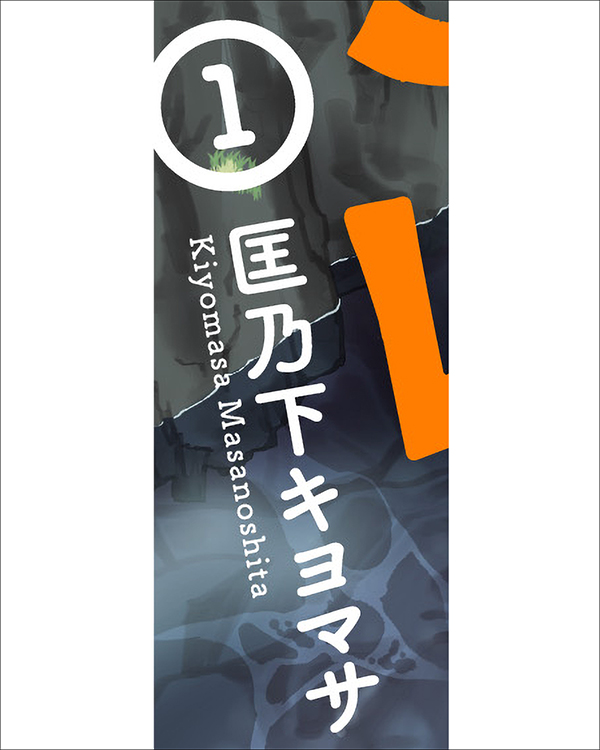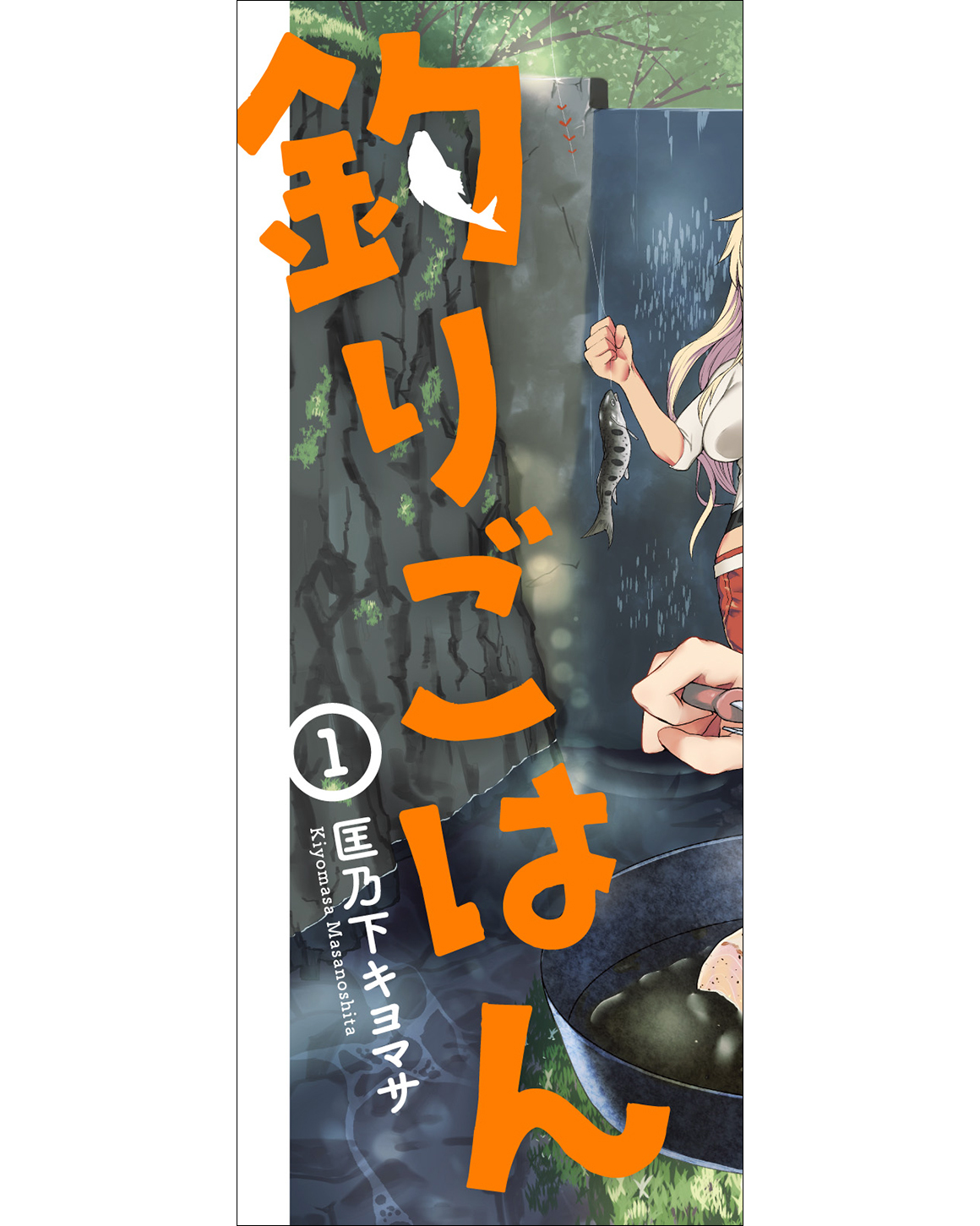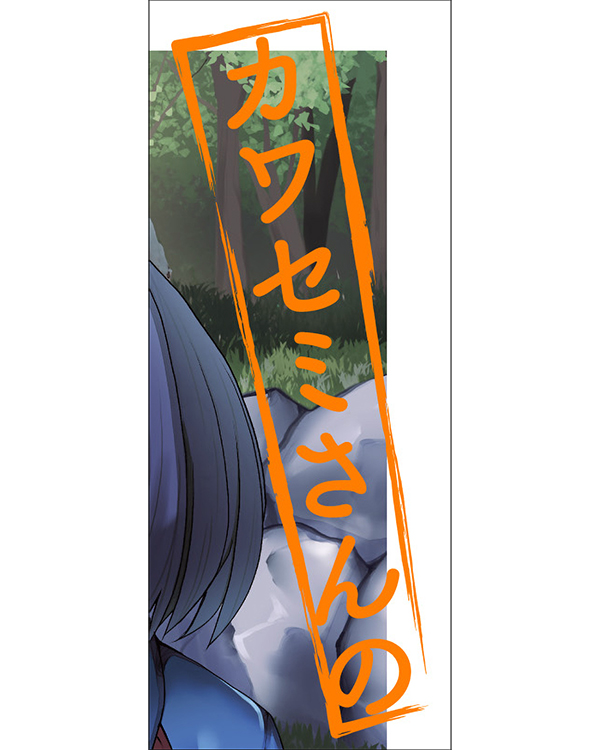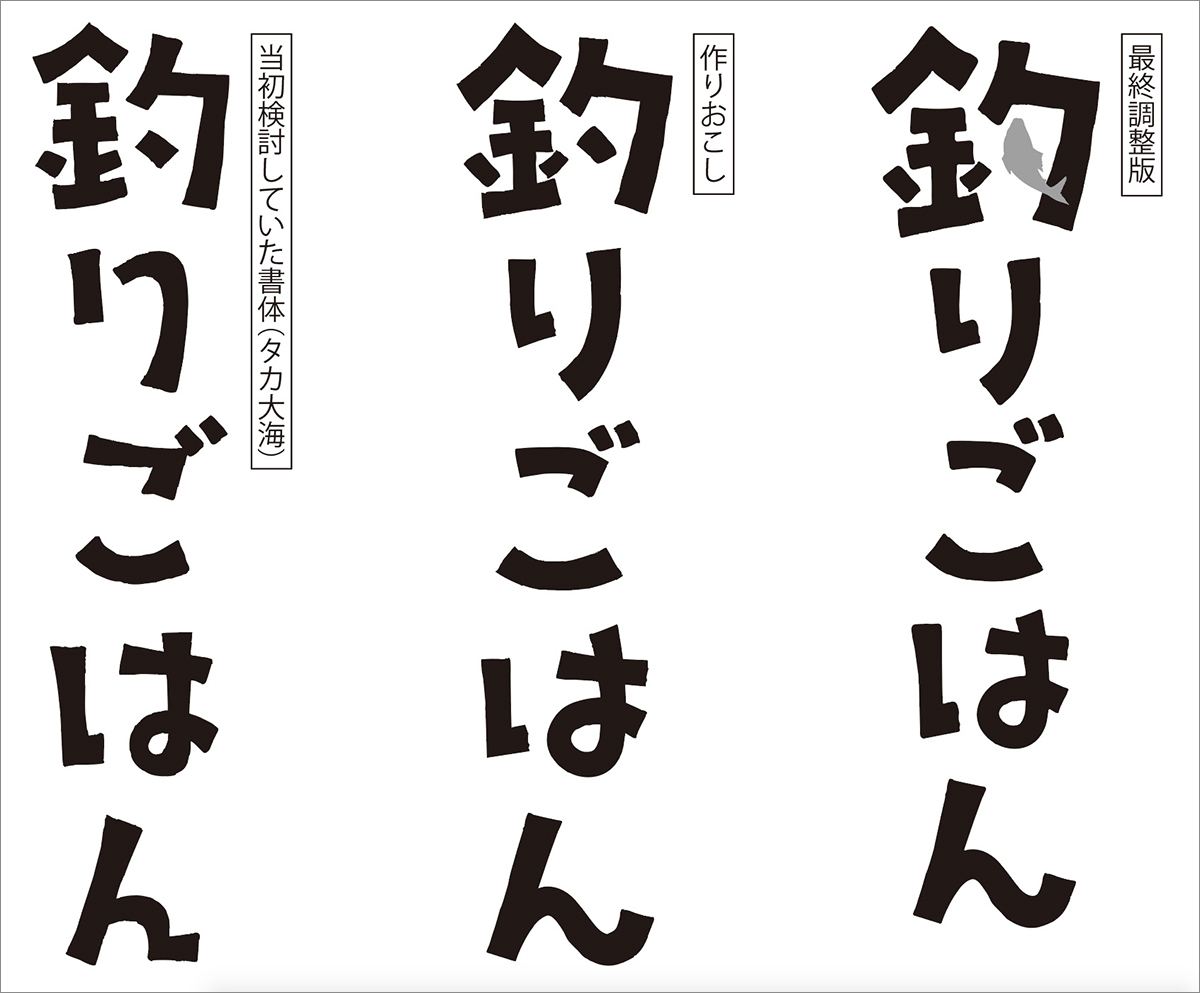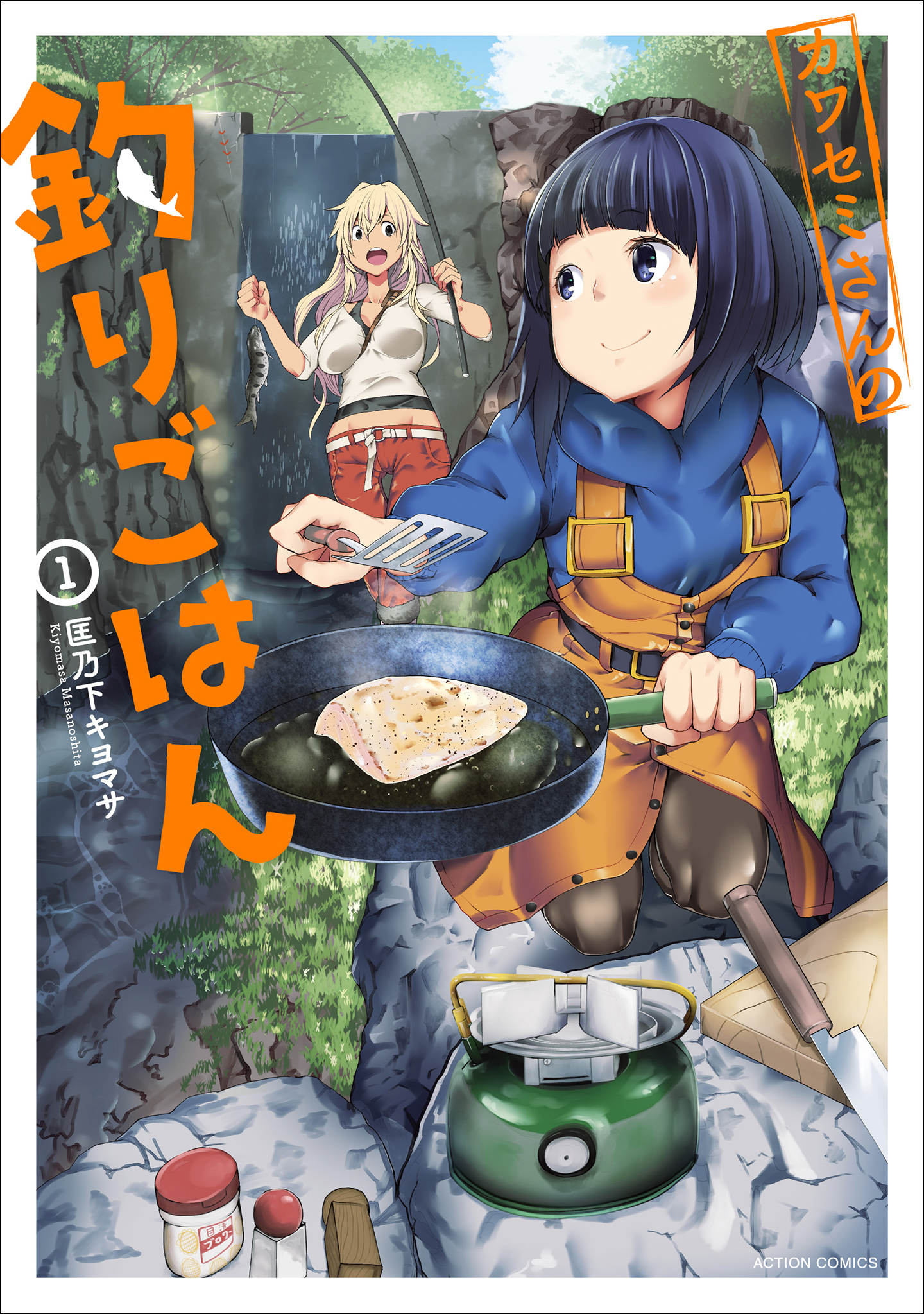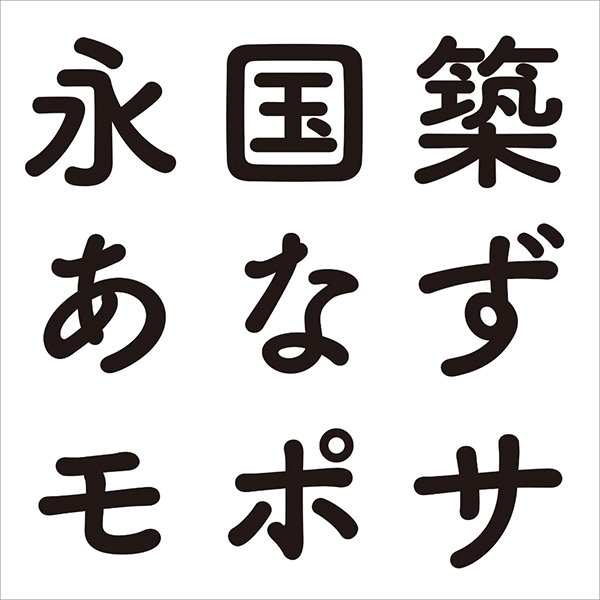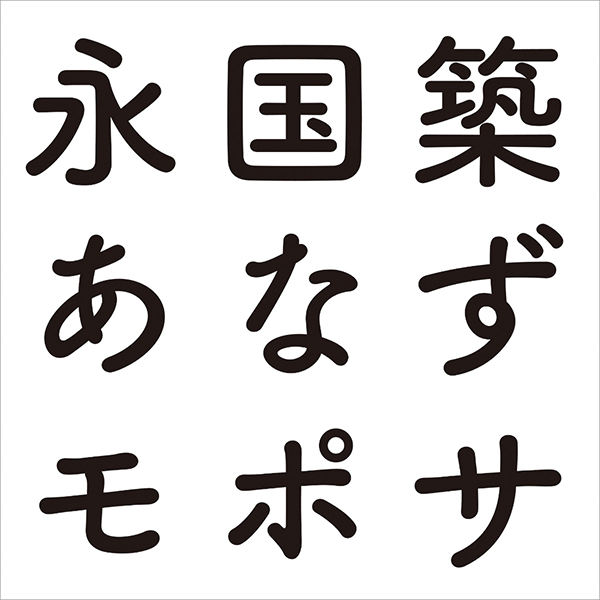
今回はコミックス『カワセミさんの釣りごはん 1』の使用フォントをご紹介。本記事はデザイン構成において重要な「フォント」の選定プロセスや加工方法を、貴重なプロの実例から紐解いてデザイン制作に役立てる連載です。
温かみのある文字で素朴かつ真摯な印象に
田舎に転校してきた内気な女子高生のカワセミが、クラスメイトのミサゴに誘われて始める「釣りごはん生活」をテーマにしたアウトドア漫画『カワセミさんの釣りごはん 1』の表紙カバー。
外見も性格も正反対の二人の関係をコミカルに描きつつ「釣り」と「料理」に真摯に向き合う作者の姿勢や作品の内容の濃さが、印象的なメインイラストと温かみのあるタイトル文字、分かりやすく素朴な味わいのあるレイアウトなどで表現されている。
Font.01「オリジナル」
アナログ的な文字で素朴な温かさを表現
タイトルのうち「釣りごはん」部分の文字は、作品の雰囲気に近い手書き風のデザイン書体「タカ大海」(タカデザインプロダクション)で仮組みした後に、よりイメージに合うよう新たに作り起こされたもの。
「釣り」や「料理」に真摯に向き合う作風を表現するため、「タカ大海」のエレメントに見られる遊び要素は控えめにしてベーシックなフォルムにし、文字の強弱でリズム感が出るよう意識して作り起こされた。タイトルの中でも鍵になる漢字の「釣」については、安定感を重視しつつ、あえて魚のシルエットをあしらうという定番技法を取り入れることで懐かしさが感じられるよう工夫されている。
Font.02「筑紫B丸ゴシック B」
コンセプトに合わせ温かく誠実な書体に
タイトルのうち「カワセミさんの」部分の文字は、クラシカルでエレガントな丸ゴシック体「筑紫B丸ゴシック B」(フォントワークス)。温かく優しい印象でありながら誠実さも感じるデザインが、素朴かつ真摯な作品にぴったりだったために選択された。
Font.03「筑紫B丸ゴシック E」
他の文字要素に合わせ優しい丸ゴシック体に
著者名部分は、表紙カバーのコンセプトや他の文字要素との相性を意識し、優しく温かみのある丸ゴシック体「筑紫B丸ゴシック E」に。著者名の欧文表記は、それより少しウェイトの細い「筑紫B丸ゴシック D」(ともにフォントワークス)が選択されている。